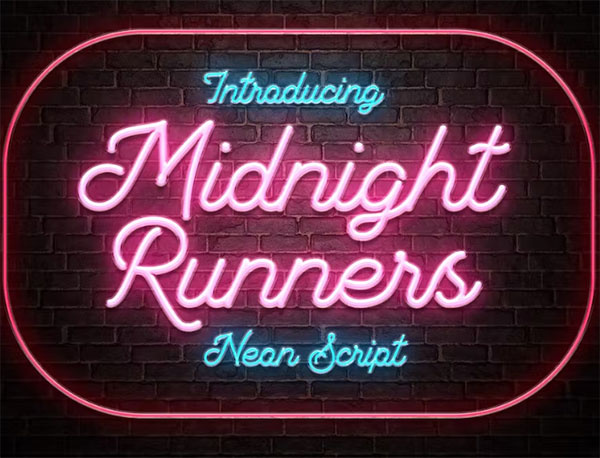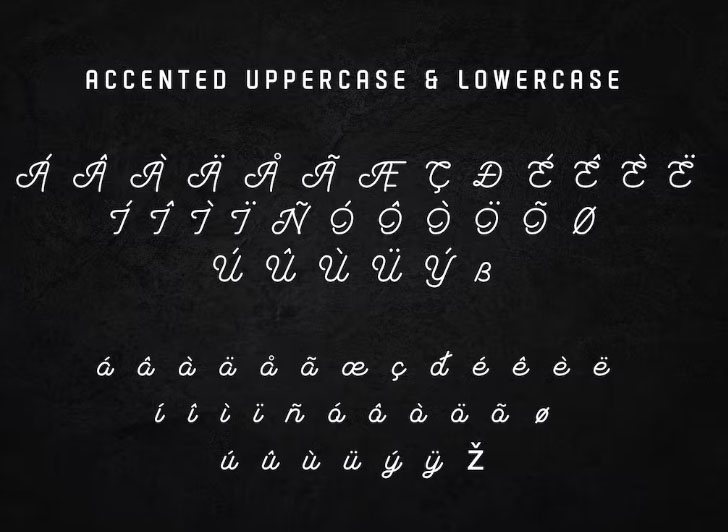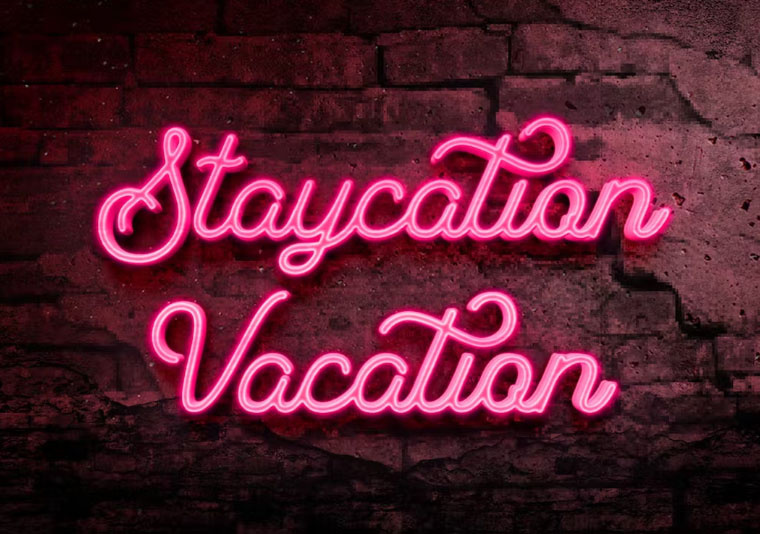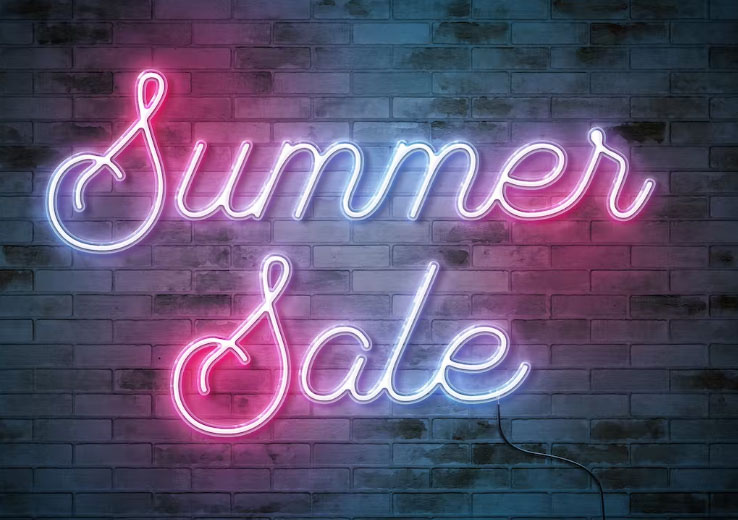
فونت رایگان انگلیسی نئون Midnight Runners
Midnight Runners یک فونت زیبای انگلیسی نئون تک خط است که بسیار مناسب برای پروژه طراحی یا برندینگ شما با استفاده از افکت متن نئون است، فونت رایگان انگلیسی نئون Midnight Runners را در ادامه مطلب از جی اف ایکس دانلود با لینک مستقیم دریافت کنید.
فونت انگلیسی نئون Midnight Runners